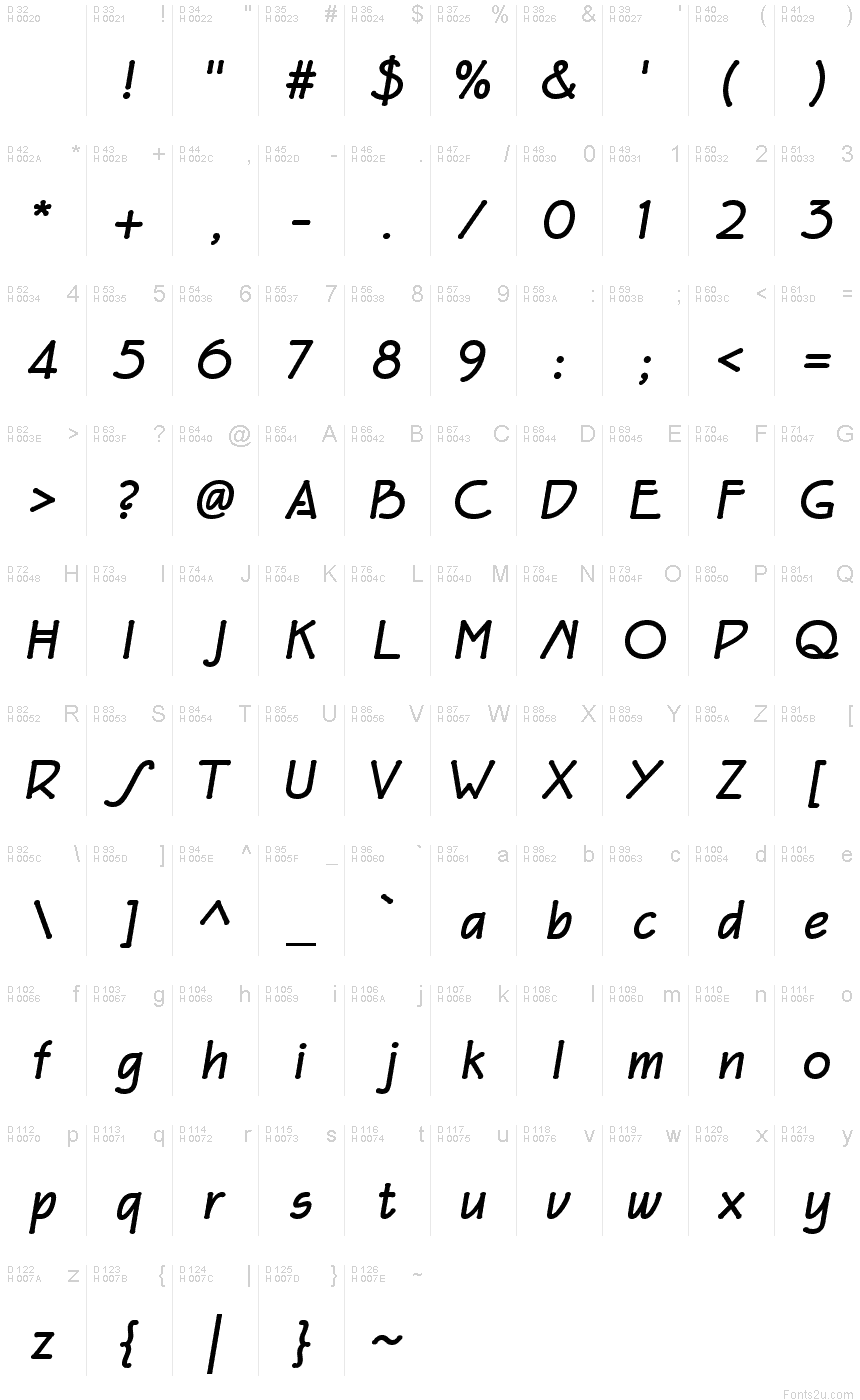
EaglefeatherFormalBoldItalic
Eaglefeather Formal Bold Italic to darmowy, bezszeryfowy krój pisma o kursywnym charakterze i płynności przypominającej pociągnięcia pędzla. Wysokie, lekko pochylone litery układają się w pewny, dynamiczny ruch, a zaokrąglone krzywizny i solidne kreski nadają całości odręczny, lecz uporządkowany i kontrolowany wygląd. Dzięki grubości bold litery zyskują wizualną gęstość, sprawiając, że słowa wyglądają konkretnie i wyraziście, a nie tylko dekoracyjnie.
Eaglefeather Formal Bold Italic nadaje projektom osobisty, a zarazem profesjonalny sznyt, co czyni ten darmowy font naturalnym wyborem do logotypów butikowych, opakowań, zaproszeń, kartek okolicznościowych, grafik w mediach społecznościowych i przyciągających wzrok nagłówków. Płynna tekstura dodaje ciepła bez utraty czytelności, zwłaszcza w średnich i większych rozmiarach. Aby uzyskać zbalansowany wygląd, warto zestawić go z prostym, neutralnym krojem bezszeryfowym w tekście uzupełniającym, dzięki czemu Eaglefeather Formal Bold Italic będzie mógł w pełni przekazać główny komunikat.